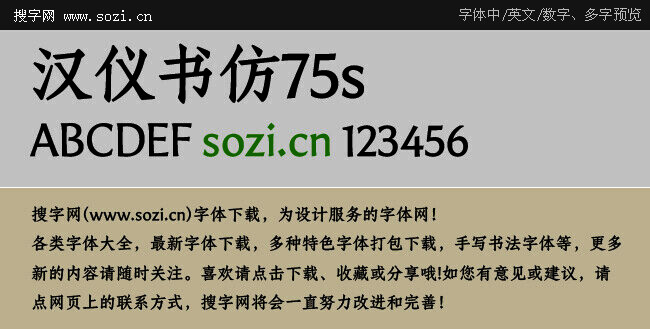
漢儀書(shū)仿75S
搜字網(wǎng)給大家提供一款漢儀書(shū)仿75S中文字體下載,漢儀書(shū)仿是一套針對(duì)正文排版使用的仿宋字體,由細(xì)到粗共5款字重。漢儀書(shū)仿家族的創(chuàng)作初衷是為了打破仿宋體現(xiàn)代應(yīng)用之困境,其結(jié)構(gòu)端穩(wěn)嚴(yán)謹(jǐn),字形呈方形,相較于仿宋體中宮略微放松、重心略低,傾斜角度較平緩,楷化的筆畫(huà)帶來(lái)了柔和的手寫(xiě)感而削弱了尖銳硬朗的刀刻感。與常規(guī)的仿宋體相比,這套字體具有更好的易讀性。適用于畫(huà)冊(cè)設(shè)計(jì)、海報(bào)設(shè)計(jì)、包裝設(shè)計(jì)等場(chǎng)合使用。(本字體為個(gè)人非商用版,如需要商用請(qǐng)聯(lián)系漢儀公司購(gòu)買版權(quán))